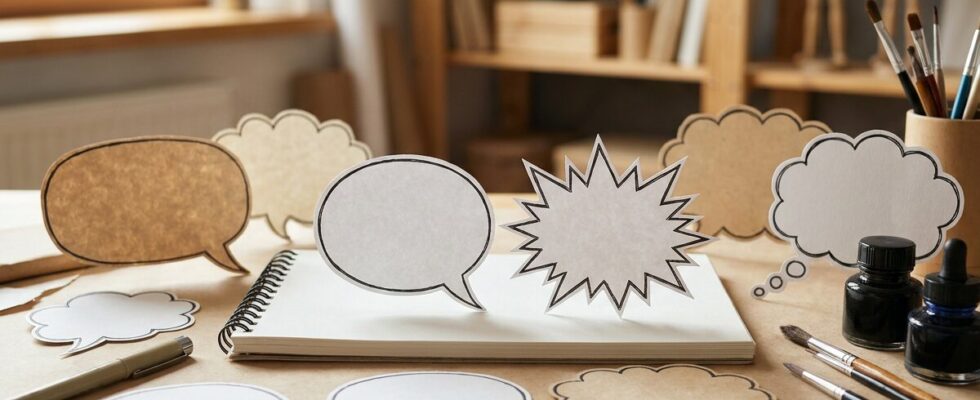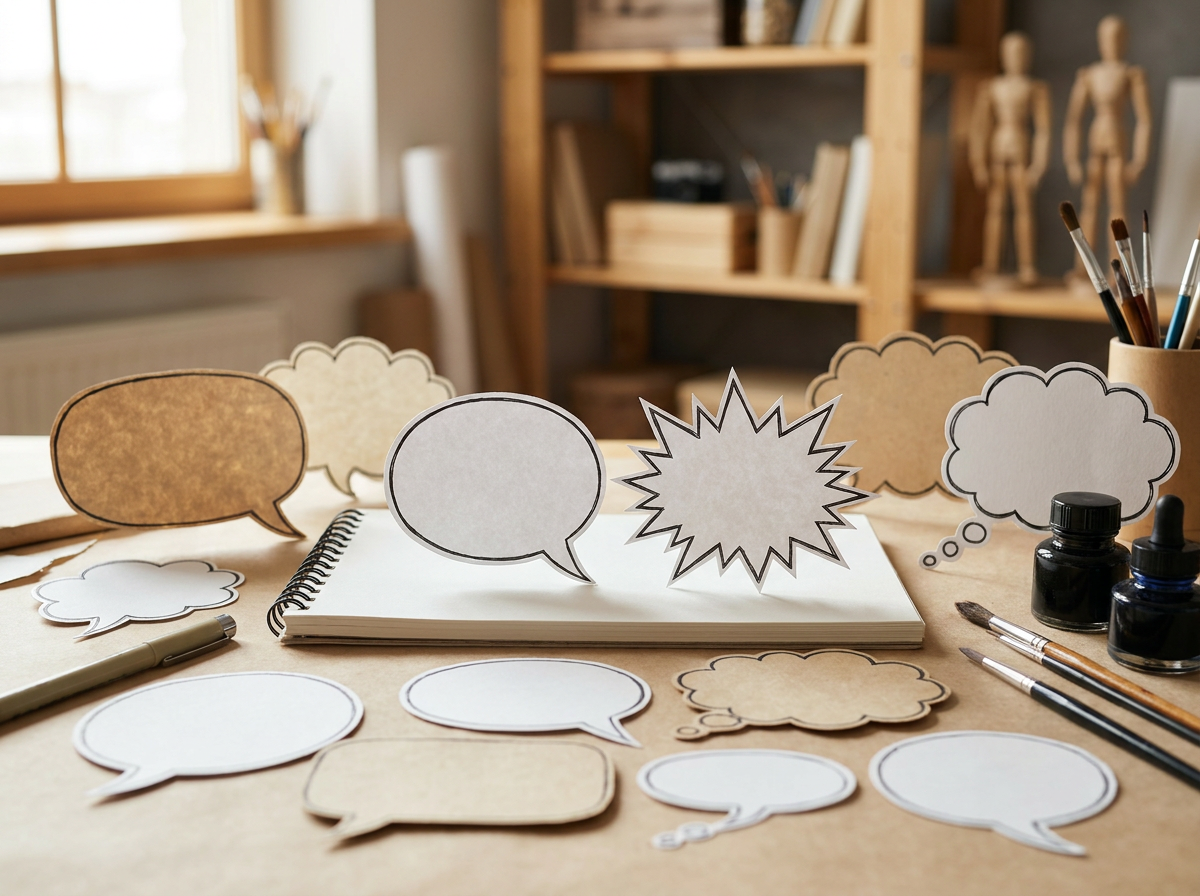
Schriftarten für Comic-Sprechblasen: Lesbarkeit und emotionaler Ausdruck
Die Wahl der richtigen Schriftart für Comic-Sprechblasen entscheidet maßgeblich über die Wirkung einer Szene. Oftmals wird die Bedeutung der Typografie unterschätzt, dabei beeinflusst sie die Stimmung und die Verständlichkeit des Dialogs erheblich. Eine unpassende Schrift kann den visuellen Fluss stören oder die beabsichtigte Emotion verfälschen. Die Herausforderung besteht darin, eine Schrift zu finden, die sowohl die Persönlichkeit der Figur widerspiegelt als auch unter verschiedenen Druckbedingungen klar lesbar bleibt. Ohne die passende Typografie wirken Sprechblasen oft flach oder gar störend. Dieser Leitfaden beleuchtet die entscheidenden Kriterien für die Auswahl von Schriftarten für Comic-Sprechblasen und zeigt, wie sich mit wenigen Handgriffen die visuelle Kommunikation optimieren lässt.Kurz zusammengefasst
- Die Wahl der Schriftart beeinflusst die emotionale Wirkung und Lesbarkeit von Comic-Dialogen.
- Serifenlose Schriften mit klaren Formen sind oft die beste Wahl für Standarddialoge.
- Spezielle Effektschriften verstärken Emotionen wie Schreien oder Flüstern.
- Die Konsistenz der Typografie über den gesamten Comic hinweg ist für die Immersion entscheidend.
Welche Kriterien sind für die Auswahl von Comic-Schriftarten entscheidend?
Die Auswahl von Schriftarten für Comic-Sprechblasen erfordert eine sorgfältige Abwägung verschiedener Faktoren, um die Lesbarkeit zu gewährleisten und die beabsichtigte emotionale Nuance präzise zu vermitteln. Entscheidend sind hierbei die Lesbarkeit unter variierenden Größen, der Zeichenabstand, die Strichstärke und die Fähigkeit, Emotionen zu transportieren. Eine Schrift muss auch bei kleineren Darstellungen auf engem Raum noch klar erkennbar sein. Der visuelle Ausdruck einer Schriftart trägt maßgeblich zur Charakterisierung einer Figur oder zur Intensivierung einer Szene bei.Lesbarkeit und Skalierbarkeit der Typografie
Die Lesbarkeit stellt das primäre Kriterium dar. Comics werden oft schnell gelesen, daher müssen die Buchstabenformen klar und eindeutig sein. Schriften mit zu vielen Details oder extremen Strichstärken erschweren die schnelle Erfassung des Textes. Besonders wichtig ist die Skalierbarkeit. Eine Schriftart, die in einem großen Panel gut aussieht, muss auch in einem kleinen Sprechblasenformat noch funktionieren. Dies betrifft sowohl die Zeichenbreite als auch den Zeilenabstand, um ein angenehmes Leseerlebnis zu ermöglichen.Emotionaler Ausdruck und Charakterisierung
Jede Schriftart besitzt eine inhärente Persönlichkeit. Eine kantige, breite Schrift kann Entschlossenheit oder Wut vermitteln, während eine weichere, abgerundete Schrift Freundlichkeit oder Sanftheit suggeriert. Die Typografie unterstützt somit die emotionale Darstellung der Charaktere. Die Charakterisierung durch Schriftarten geht über bloße Emotionen hinaus. Ein Roboter könnte eine monospace-Schrift verwenden, ein Magier eine verschnörkelte. Solche Entscheidungen vertiefen die Immersion und geben dem Leser zusätzliche visuelle Hinweise zur Figur.Konsistenz und Stilbruch
Die Konsistenz der Schriftarten über den gesamten Comic hinweg ist für ein professionelles Erscheinungsbild unerlässlich. Ein plötzlicher, unbegründeter Wechsel der Schriftart kann den Lesefluss stören und die Glaubwürdigkeit der Erzählung untergraben. Gleichzeitig kann ein bewusster Stilbruch, beispielsweise durch eine besonders markante Schrift bei einem Ausruf, eine gezielte dramatische Wirkung erzielen. Dies erfordert jedoch ein feines Gespür für den richtigen Moment und die passende Intensität.Welche Schriftarten eignen sich für Standarddialoge in Comics?
Für Standarddialoge in Comic-Sprechblasen bewähren sich in der Praxis vor allem serifenlose Schriften, die eine hohe Lesbarkeit und eine neutrale Ästhetik aufweisen. Diese Schriften ermöglichen eine schnelle Erfassung des Textes, ohne den visuellen Fokus von den Zeichnungen abzulenken. Die Wahl fällt oft auf Varianten, die speziell für den Einsatz in Comics entwickelt wurden.Kurz gesagt: Für Standarddialoge in Comics sind serifenlose Schriften mit hoher Lesbarkeit und neutraler Ästhetik, wie Comic Sans MS, Anime Ace oder Blambot-Schriften, die beste Wahl, da sie den Lesefluss fördern und die Aufmerksamkeit auf die Illustrationen lenken.
Bewährte serifenlose Optionen
Comic Sans MS ist zwar oft kritisiert, erfüllt aber den Zweck in Comics aufgrund ihrer informellen, handgeschriebenen Anmutung. die weichen Formen und der lockere Zeichenabstand tragen zur guten Lesbarkeit bei. Eine weitere beliebte Wahl ist Anime Ace, die eine klare, aber dennoch dynamische Ästhetik bietet. wird häufig in Manga-Übersetzungen verwendet und zeichnet sich durch die Vielseitigkeit aus.Spezialisierte Comic-Schriften
Viele Comic-Künstler greifen auf spezialisierte Schriften von Anbietern wie Blambot zurück. Diese sind explizit für den Comic-Einsatz konzipiert und bieten oft eine breite Palette an Stilen und Gewichten, die für verschiedene Dialogtypen optimiert sind. Solche Schriften berücksichtigen Aspekte wie die Optimierung für kleine Größen und die Vermeidung von Leseschwierigkeiten, die bei generischen Schriften auftreten können. sind meist robuster und flexibler im Einsatz.Praxis-Tipp
Experimentieren mit verschiedenen Schriftgrößen und -stärken innerhalb einer Familie, um die optimale Balance zwischen Lesbarkeit und visuellem Impact zu finden. Ein leicht erhöhter Zeilenabstand kann die Lesbarkeit in engen Sprechblasen verbessern.
Alternativen zu den Klassikern
Neben den etablierten Optionen gibt es zahlreiche Alternativen, die eine ähnliche Ästhetik bieten, aber möglicherweise eine frischere oder individuellere Note verleihen. Dazu gehören beispielsweise Schriften wie „Komika Text“ oder „Bangers“. Die Auswahl sollte stets auf ausgiebigen Tests basieren. Ein Probedruck in verschiedenen Größen und auf unterschiedlichen Papiersorten offenbart oft Schwächen, die am Bildschirm nicht sichtbar waren.Wie können Effektschriften die Emotionen in Sprechblasen verstärken?
Effektschriften sind ein mächtiges Werkzeug, um die emotionale Intensität von Dialogen in Comic-Sprechblasen zu steigern und spezifische Stimmungen zu transportieren. brechen bewusst mit der neutralen Ästhetik von Standarddialogschriften, um Schreie, Flüstern, Gedanken oder andere besondere Ausdrucksformen visuell zu untermauern. Die Kunst liegt darin, sie sparsam und gezielt einzusetzen.Schreie und laute Ausrufe
Für Schreie oder laute Ausrufe eignen sich Schriften mit kräftigen, oft unregelmäßigen Strichstärken und scharfen Kanten. Beispiele hierfür sind „Badaboom BB“ oder „Mighty Mouth“. Diese Schriften vermitteln Dringlichkeit und Lautstärke. Oftmals werden diese Effektschriften zusätzlich mit Großbuchstaben und Ausrufezeichen kombiniert, um die visuelle Wirkung zu maximieren. Eine rote oder orangefarbene Schriftfarbe kann die Intensität weiter erhöhen.Flüstern und Geheimnisse
Das Gegenteil von Schreien ist das Flüstern, welches durch dünne, oft kursive oder leicht zittrige Schriften dargestellt wird. „Whisper“ oder „Secret Agent“ sind Beispiele für Typen, die eine leise, konspirative Atmosphäre schaffen. Manchmal wird auch eine sehr kleine Schriftgröße in einer grauen Sprechblase verwendet, um den Eindruck von gedämpfter Sprache zu erzeugen. Die Subtilität der Darstellung ist hier entscheidend.⇄ Vergleich auf einen Blick
| Einsatzbereich | Standarddialog | Emotionaler Ausdruck |
|---|---|---|
| Lesbarkeit | ●●●●● | ●●●○○ |
| Neutralität | ●●●●○ | ●○○○○ |
| Visueller Impact | ●●○○○ | ●●●●● |
| Vielseitigkeit | ●●●●○ | ●●○○○ |
Gedanken und innere Monologe
Für Gedanken oder innere Monologe werden oft Schriften verwendet, die eine schreibmaschinenähnliche oder leicht unregelmäßige Anmutung haben. „Thought Bubble“ oder „Mental Block“ können hier zum Einsatz kommen. Die Sprechblase selbst ist dabei oft wolkig oder gestrichelt. Die Farbe der Schrift kann ebenfalls eine Rolle spielen; ein leicht bläulicher oder violetter Ton kann die introspektive Natur von Gedanken unterstreichen. Die Kombination aus Schrift und Blasenform schafft eine kohärente Darstellung.Welche typografischen Fehler sollten bei Comic-Sprechblasen vermieden werden?
Typografische Fehler in Comic-Sprechblasen können die Lesbarkeit erheblich beeinträchtigen und die professionelle Wirkung eines Comics mindern. Selbst kleine Unachtsamkeiten stören den Lesefluss und lenken von der eigentlichen Geschichte ab. Die Vermeidung dieser Fallstricke ist entscheidend für eine gelungene visuelle Kommunikation.Überladung und Unübersichtlichkeit
Ein häufiger Fehler ist die Überladung der Sprechblase mit zu viel Text. Dies führt zu einer zu kleinen Schriftgröße oder einem zu engen Zeilenabstand, was die Lesbarkeit drastisch reduziert. Der Text sollte prägnant formuliert sein. Die Unübersichtlichkeit entsteht auch durch die Verwendung von zu vielen unterschiedlichen Schriftarten in einem Panel oder auf einer Seite. Eine klare Hierarchie und eine begrenzte Auswahl an Schriften sind für die visuelle Harmonie unerlässlich.Mythos vs. Fakt
Mythos
Comic Sans MS ist eine unprofessionelle Schriftart und sollte niemals verwendet werden.
Fakt
Obwohl oft verspottet, ist Comic Sans MS für den ursprünglichen Zweck – informelle Comics – aufgrund ihrer Lesbarkeit und handgeschriebenen Ästhetik durchaus geeignet.
Falsche Betonung und fehlende Hierarchie
Die falsche Betonung durch übermäßigen Einsatz von Fettdruck, Kursivschrift oder Großbuchstaben kann die beabsichtigte Wirkung ins Gegenteil verkehren. Jede Hervorhebung sollte einen klaren Zweck erfüllen und sparsam eingesetzt werden. Eine fehlende Hierarchie zwischen Standarddialog und Effektschriften verwirrt den Leser. Es muss klar erkennbar sein, wann eine Figur normal spricht und wann eine besondere Emotion oder ein Geräusch dargestellt wird.Technische Mängel und Druckprobleme
Technische Mängel wie unzureichende Auflösung der Schrift oder falsche Dateiformate können zu pixeligen oder unscharfen Texten führen. Dies ist besonders bei der Druckvorbereitung zu beachten, um ein klares Ergebnis zu erzielen. Druckprobleme entstehen oft durch zu dünne Linien oder zu geringen Kontrast zwischen Schrift und Hintergrund. Ein Probedruck ist hier unerlässlich, um sicherzustellen, dass der Text auch auf Papier optimal lesbar ist.Welche Rolle spielt die Sprechblasenform für die Textdarstellung?
Die Form der Sprechblase ist nicht nur ein dekoratives Element, sondern ein integraler Bestandteil der visuellen Kommunikation in Comics. beeinflusst, wie der Text wahrgenommen wird, und kann zusätzliche Informationen über den Sprecher oder die Art des Gesagten vermitteln. Eine durchdachte Gestaltung der Sprechblase unterstützt die Typografie und verstärkt die narrative Wirkung.Standardformen und die Bedeutung
Die ovale oder runde Sprechblase ist die gängigste Form für normale Dialoge. vermittelt eine neutrale, fließende Kommunikation und lenkt nicht vom Inhalt ab. Der Text passt sich organisch der Form an. Eine rechteckige oder eckige Sprechblase kann eine direktere, manchmal auch autoritärere oder sachlichere Aussage signalisieren. wird oft für Erzählerstimmen oder technische Erklärungen verwendet.Spezielle Formen für emotionale Nuancen
Für Gedanken wird häufig eine wolkige Sprechblase eingesetzt, die eine introspektive oder träumerische Stimmung erzeugt. Die Textplatzierung innerhalb dieser Form ist oft freier und weniger strukturiert. Eine gezackte oder explosive Sprechblase signalisiert Schreie, Wut oder laute Geräusche. Die scharfen Kanten verstärken die visuelle Dramatik und unterstreichen die Intensität des Gesagten.Wichtig zu wissen
Die Kombination aus Schriftart und Sprechblasenform muss harmonieren. Eine aggressive Schrift in einer sanften Wolkenblase wirkt ebenso deplatziert wie eine zarte Schrift in einer gezackten Ausrufblase. Kohärenz ist entscheidend.
Textfluss und Platzierung
Der Textfluss innerhalb der Sprechblase sollte natürlich und leicht lesbar sein. Eine zu enge Sprechblase oder eine ungeschickte Zeilenumbruchführung kann den Lesefluss stören. Der Text sollte den Raum optimal ausnutzen, ohne gequetscht zu wirken. Die Platzierung der Sprechblase im Panel ist ebenfalls von Bedeutung. sollte den Blick des Lesers durch das Panel leiten und nicht wichtige Bilddetails verdecken. Die Größe der Sprechblase muss proportional zur Schriftgröße sein.Wie beeinflusst die Digitalisierung die Auswahl und Nutzung von Comic-Schriftarten?
Die Digitalisierung hat die Landschaft der Comic-Produktion grundlegend verändert und damit auch die Auswahl und Nutzung von Schriftarten für Sprechblasen. Digitale Tools und eine Fülle an verfügbaren Ressourcen ermöglichen eine größere Experimentierfreude, stellen aber auch neue Anforderungen an die Typografie. Die Möglichkeiten der Anpassung und die globale Verfügbarkeit sind dabei zentrale Aspekte.Zugang zu einer breiteren Schriftbibliothek
Die digitale Ära bietet einen unvergleichlichen Zugang zu einer riesigen Bibliothek an Schriftarten. Viele Designer und Künstler stellen die Kreationen online zur Verfügung, oft sogar kostenlos für den nicht-kommerziellen Gebrauch. Dies erweitert die kreativen Optionen erheblich. Früher waren Comic-Künstler auf eine begrenzte Auswahl an physischen Letraset-Bögen oder teure Lizenzschriften angewiesen. Heute lässt sich aus Tausenden von digitalen Fonts wählen, die spezifisch für Comics entwickelt wurden.Software-Tools und Anpassungsmöglichkeiten
Moderne Grafiksoftware wie Adobe Photoshop, Illustrator oder Clip Studio Paint bieten umfangreiche Funktionen zur Textbearbeitung. Dazu gehören präzise Kontrolle über Kerning, Zeilenabstand und die Möglichkeit, Schriften zu verformen oder mit Effekten zu versehen. Diese Anpassungsmöglichkeiten erlauben es, Schriften perfekt an die Sprechblasenform anzupassen und subtile visuelle Nuancen zu erzeugen, die manuell kaum umsetzbar wären. Die digitale Bearbeitung beschleunigt den Workflow erheblich.Kostenüberblick
Kostenlose Fonts:
0 €
Lizenzierte Fonts:
20 – 200 € pro Lizenz
Stand: 2026, Angaben ohne Gewähr
Herausforderungen im digitalen Workflow
Trotz der Vorteile bringt die Digitalisierung auch Herausforderungen mit sich. Die schiere Menge an verfügbaren Schriften kann die Auswahl erschweren. Zudem müssen Lizenzfragen bei der kommerziellen Nutzung beachtet werden. Die Kompatibilität von Schriftarten zwischen verschiedenen Systemen und Programmen ist ebenfalls ein wichtiger Aspekt. Eine Schrift, die auf einem System perfekt aussieht, kann auf einem anderen Darstellungsprobleme verursachen.Häufige Fragen
Welche Schriftarten eignen sich am besten für Comic-Sprechblasen?
Für Comic-Sprechblasen eignen sich besonders gut serifenlose Schriftarten mit einer klaren, gut lesbaren Form. Beispiele hierfür sind Comic Sans MS (trotz seiner Kontroversen), Komika Title, Blambot Fonts oder auch klassische Schriften wie Arial oder Helvetica, die entsprechend angepasst werden können.
Warum ist die Lesbarkeit bei Comic-Schriftarten so wichtig?
Die Lesbarkeit ist entscheidend, da Comic-Sprechblasen oft kurze, prägnante Dialoge enthalten, die schnell erfasst werden müssen. Eine schwer lesbare Schriftart kann den Lesefluss stören und die Immersion in die Geschichte beeinträchtigen.
Sollten Großbuchstaben oder Kleinbuchstaben verwendet werden?
Traditionell werden in Comic-Sprechblasen häufig Großbuchstaben verwendet, da sie eine stärkere visuelle Präsenz haben und in kleineren Größen besser lesbar sein können. Moderne Comics experimentieren jedoch auch mit Kleinbuchstaben, um bestimmte Stimmungen oder Charaktereigenschaften zu unterstreichen.
Gibt es kostenlose Schriftarten für den kommerziellen Gebrauch?
Ja, es gibt zahlreiche kostenlose Schriftarten, die auch für den kommerziellen Gebrauch lizenziert sind. Plattformen wie Font Squirrel, DaFont (mit Filteroption für kommerzielle Nutzung) oder Google Fonts bieten eine große Auswahl. Es ist jedoch stets wichtig, die Lizenzbedingungen jeder einzelnen Schriftart sorgfältig zu prüfen.
Wie kann die Schriftart die Stimmung eines Comics beeinflussen?
Die Wahl der Schriftart kann maßgeblich zur emotionalen Wirkung eines Comics beitragen. Eine schroffe, eckige Schrift kann Wut oder Entschlossenheit ausdrücken, während eine weichere, rundere Schrift Freundlichkeit oder Sanftheit vermitteln kann. Auch die Größe, der Zeilenabstand und die Farbe der Schrift spielen eine Rolle bei der Stimmungsgestaltung.